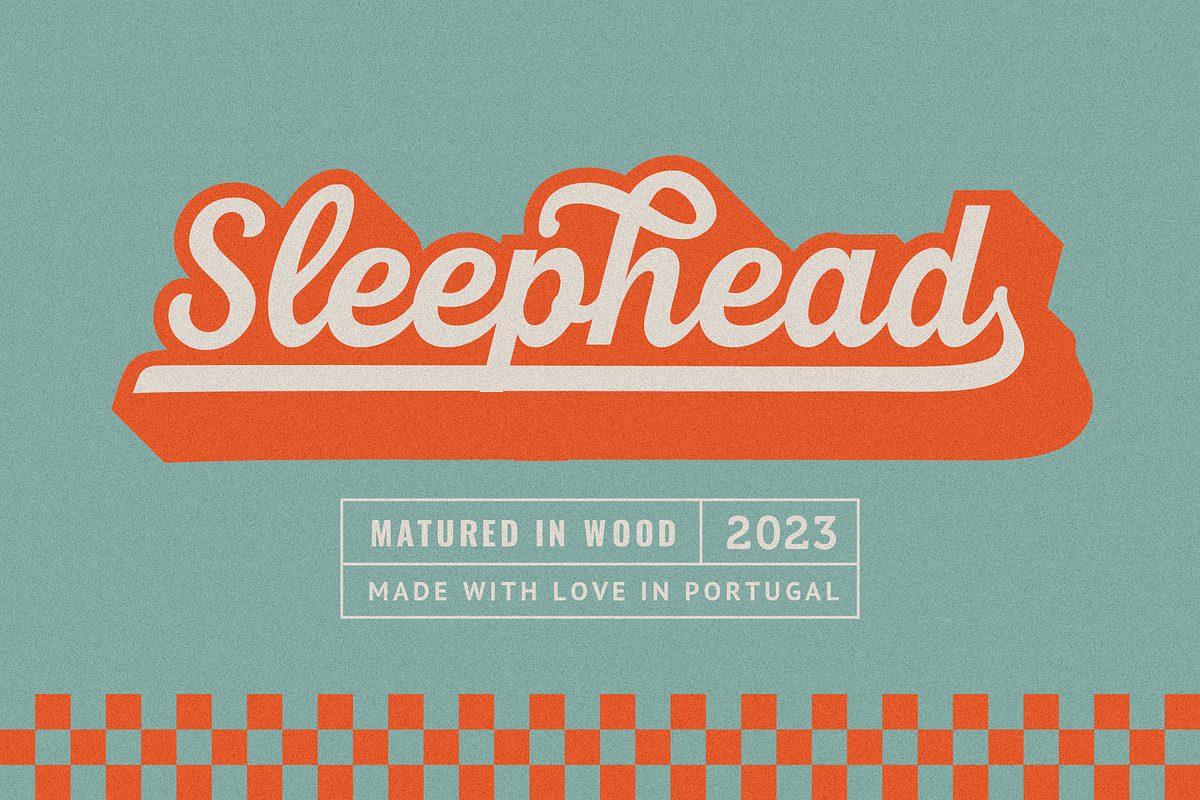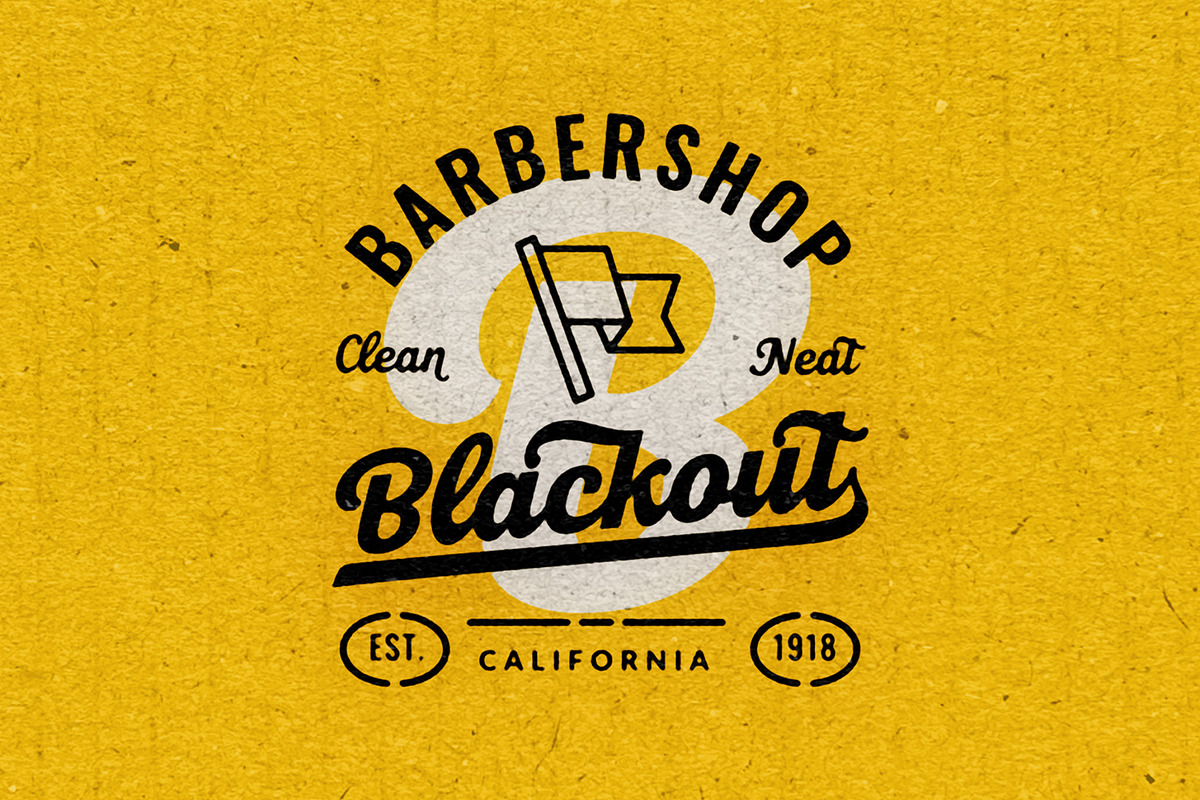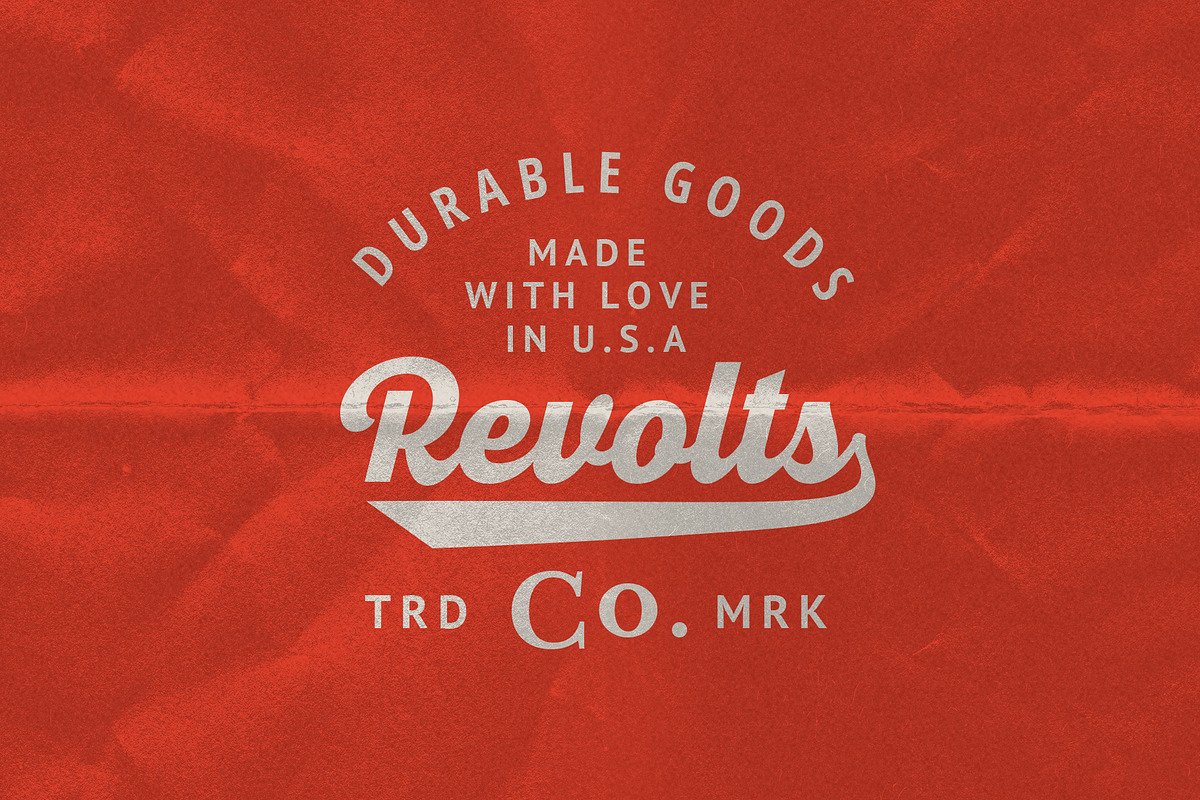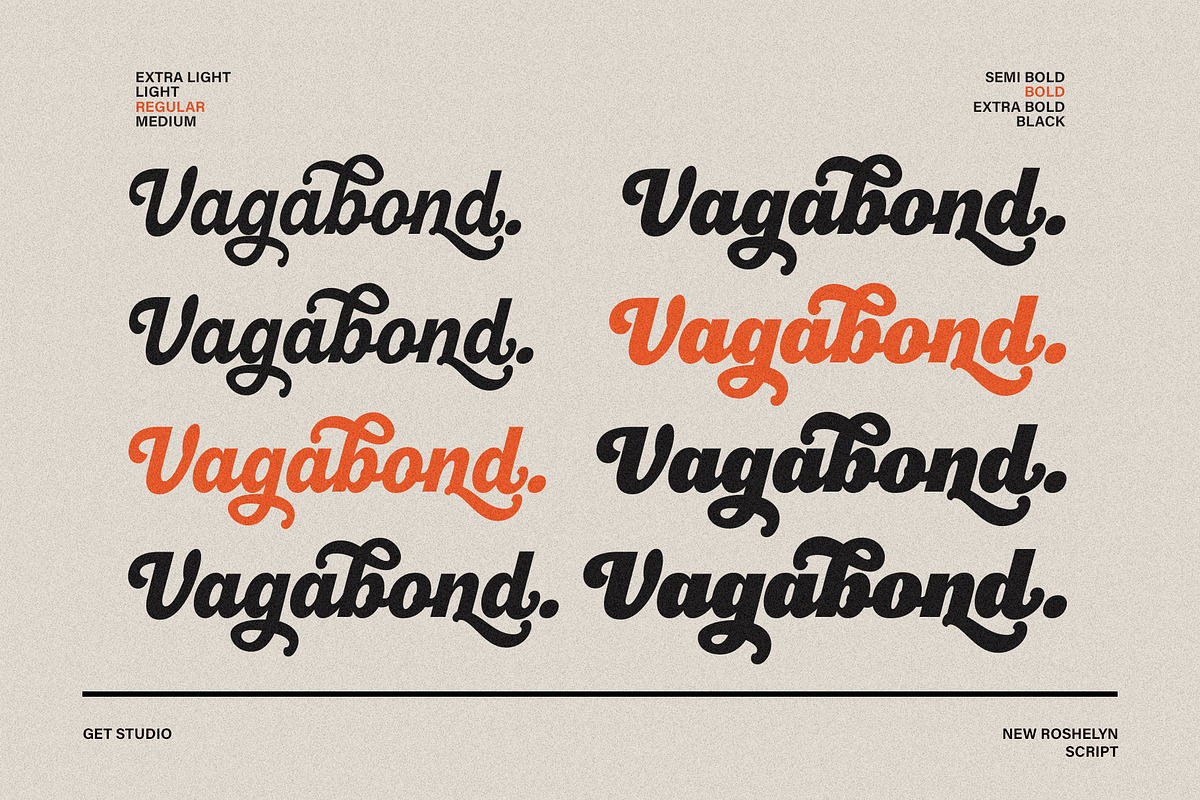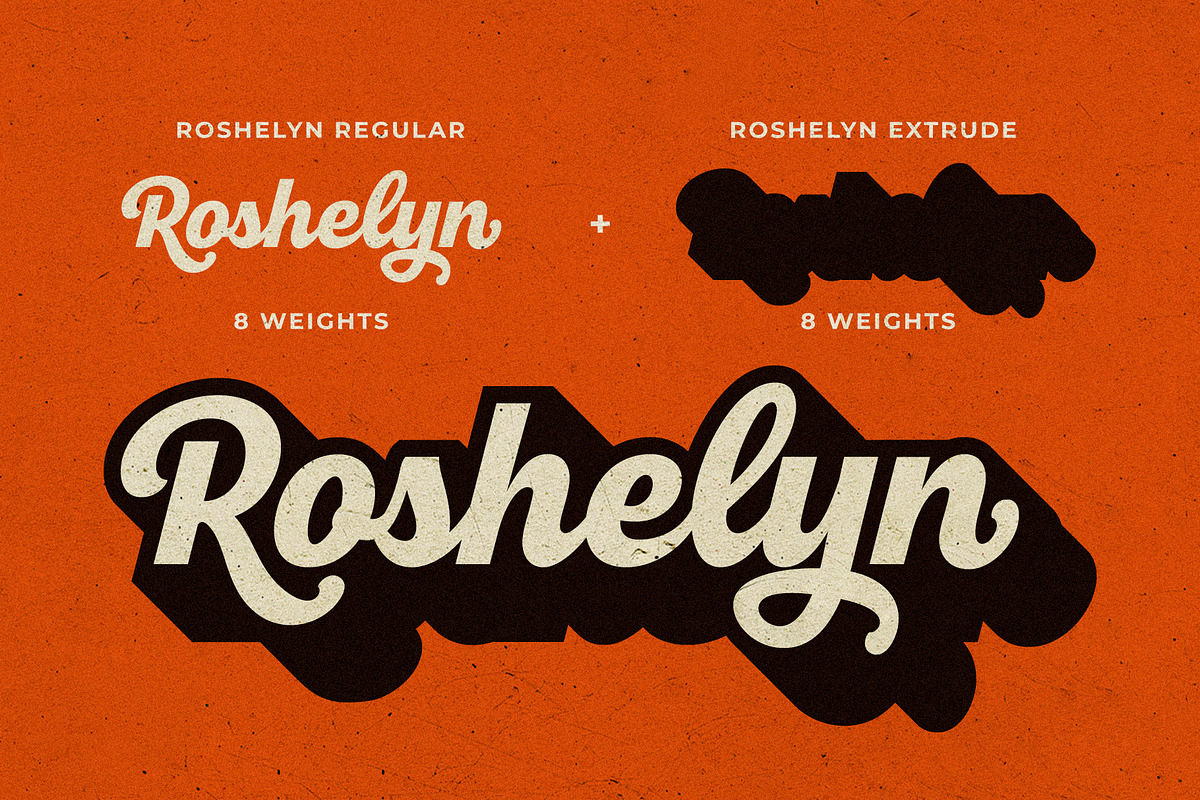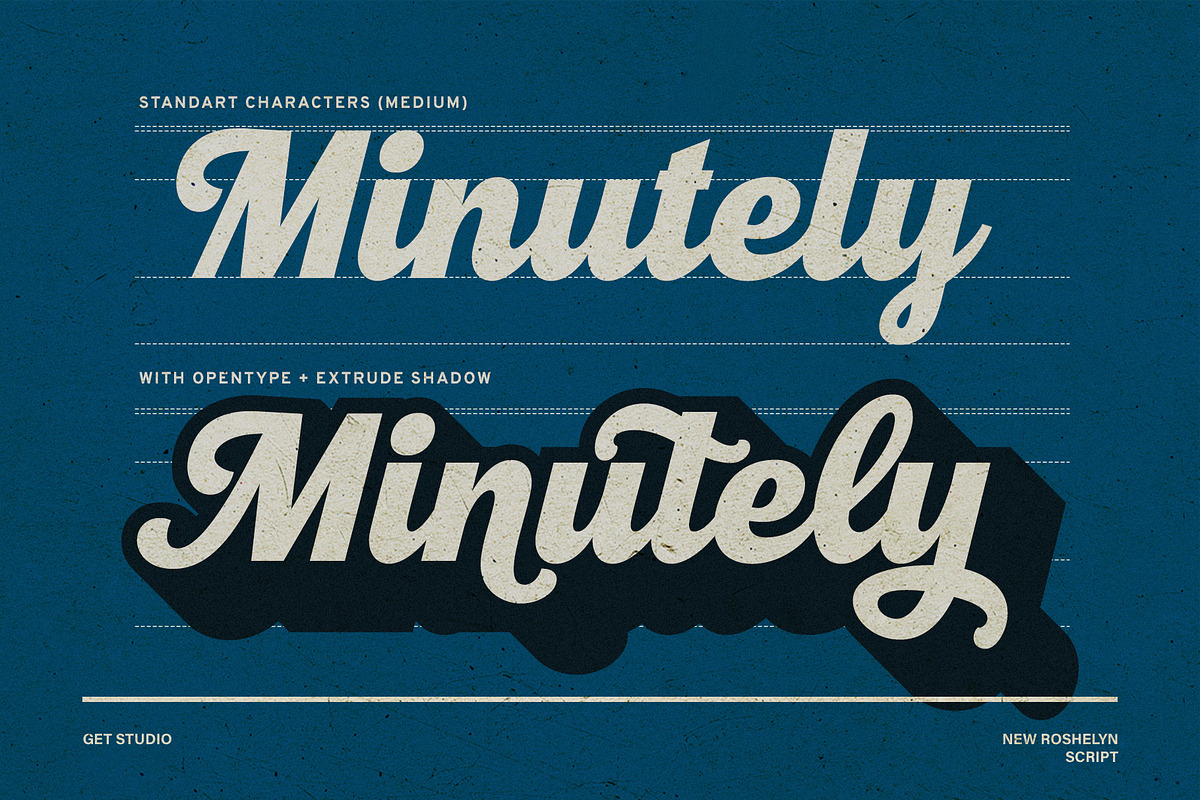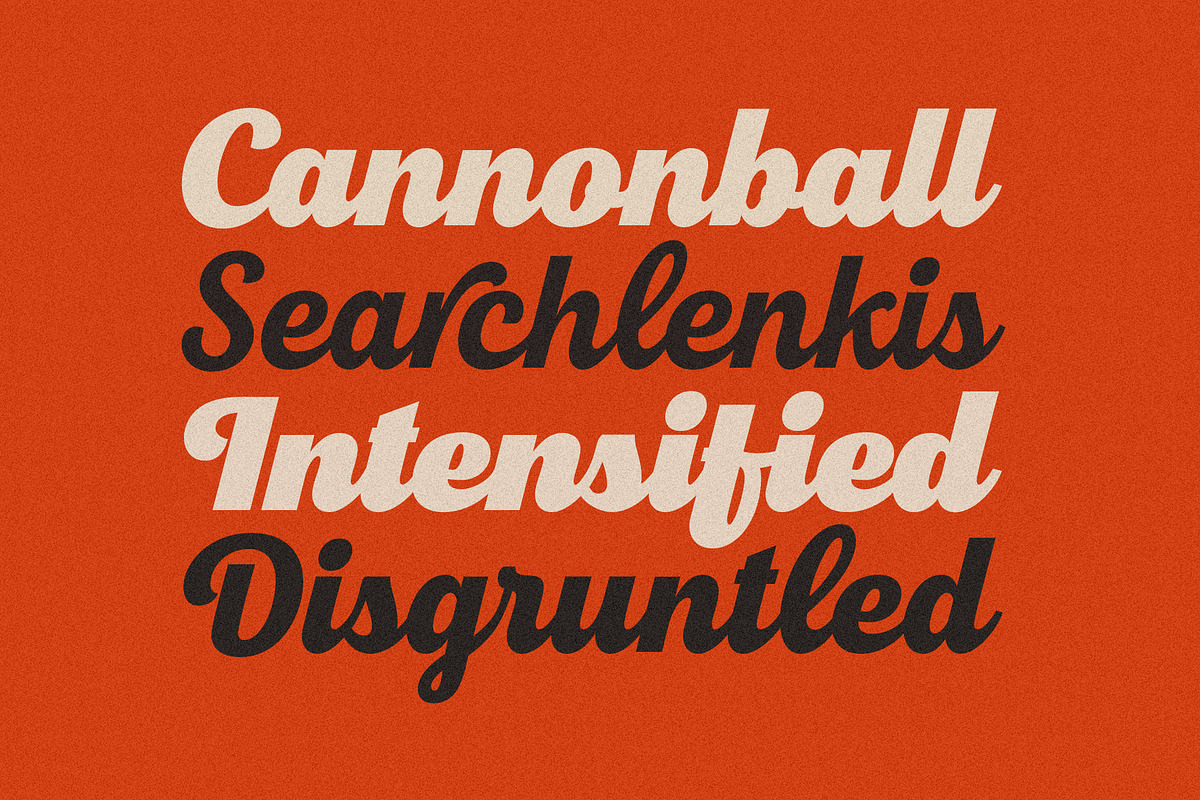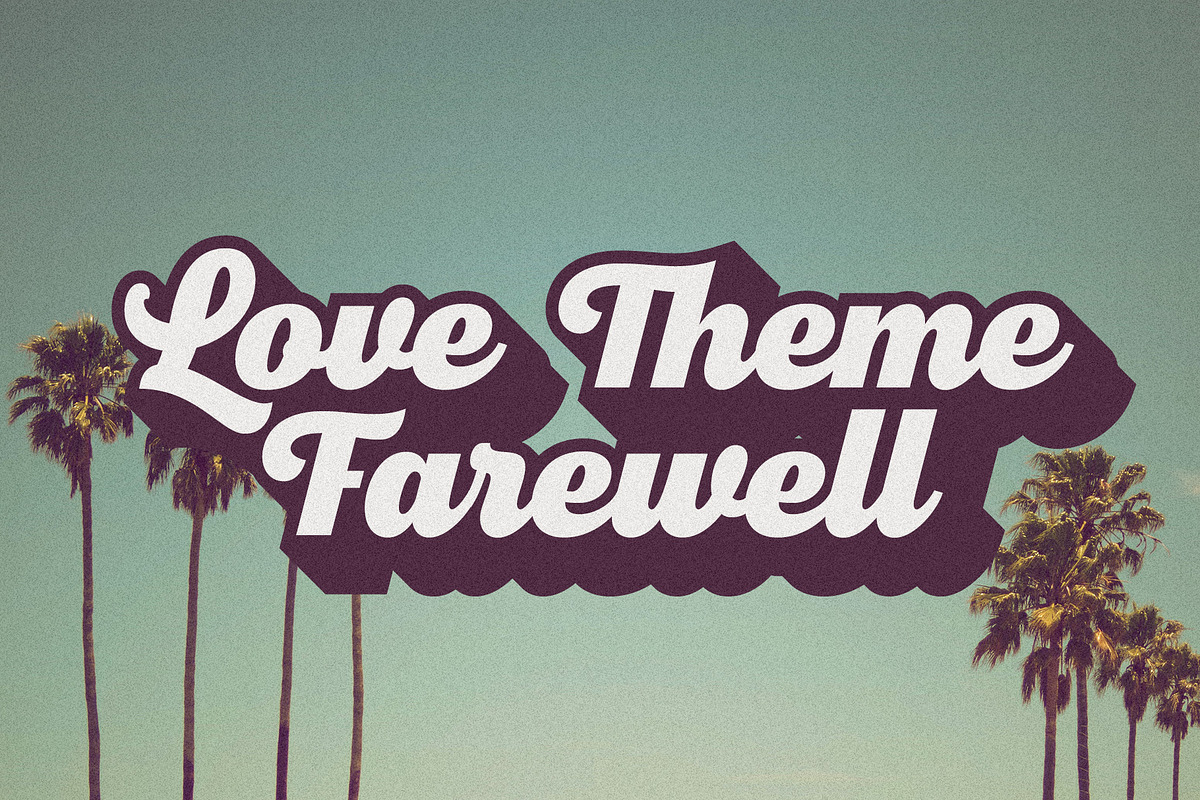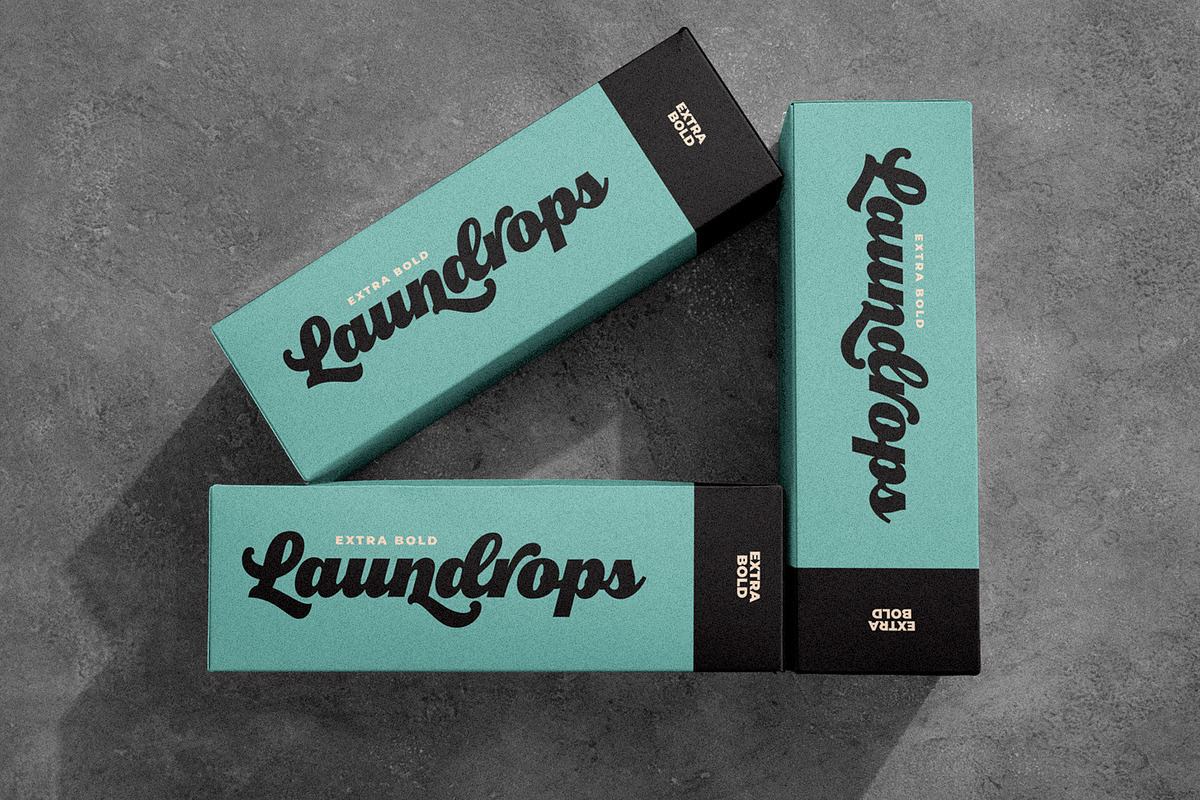
New Roshelyn Script – Font Family
New Roshelyn – Font Script Retro Elegan dengan Ekstra Gaya & Kepribadian
Perkenalkan New Roshelyn Font Family, jenis huruf script yang dirancang dengan cermat dan proporsi lengkung yang seimbang. Font ini memiliki kepribadian khas yang membuat setiap desain tampil unik dan menawan. Dilengkapi dengan versi Extrude dan Swash Tail, New Roshelyn juga menghadirkan nuansa retro yang klasik dan berkelas.
Sangat cocok digunakan untuk berbagai kebutuhan desain seperti logo, badge, kemasan produk, headline, poster, kaos, kartu ucapan, hingga undangan pernikahan.
✨ Fitur Unggulan:
• Huruf mengalir alami yang ideal untuk menciptakan pesan yang menarik
• Banyak alternatif karakter & ligatur untuk hasil desain yang lebih dinamis
• Termasuk fitur OpenType: Stylistic Alternates, Stylistic Sets, dan Ligatures
• New Roshelyn Script Regular
• Versi Extrude untuk efek 3D klasik
• Swash Tail untuk aksen dekoratif tambahan